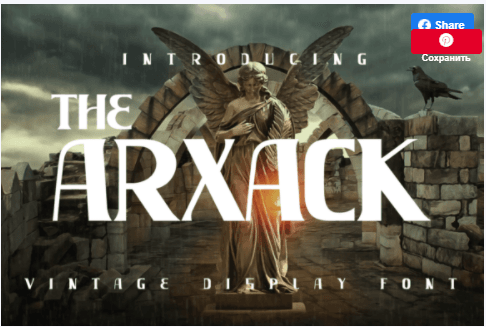
The Arxack Font
Arxack - это крутой, жирный шрифт в винтажном стиле. Его можно использовать для различных целей, таких как логотипы, заголовки, футболки, фирменные бланки, вывески, этикетки, новости, плакаты, значки и многое другое.